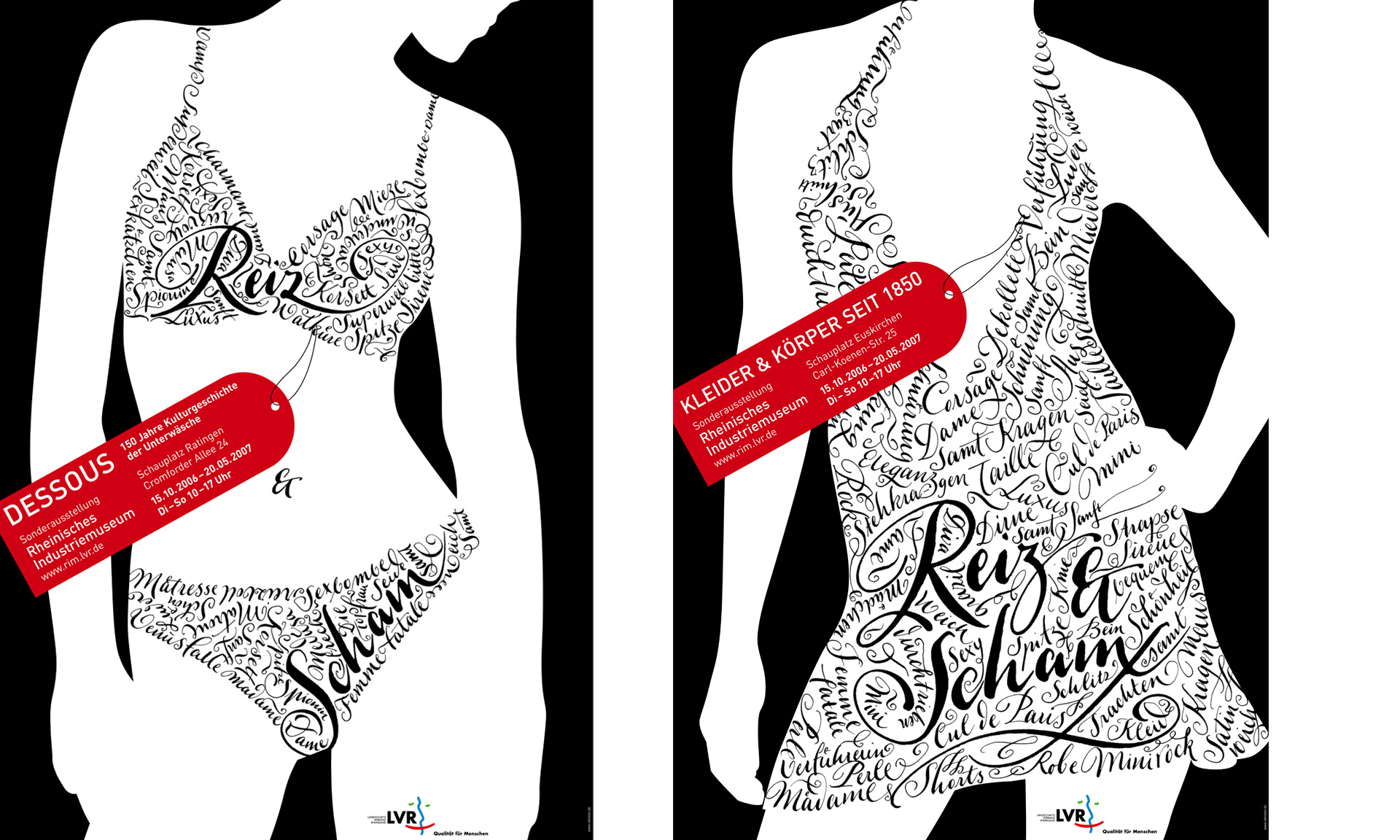
Reiz & Scham Ausstellungsplakate
Konzeption und Gestaltung:
Oktober Kommunikationsdesign, Bochum
Leistung:
Kalligrafische Umsetzung der Wäschestücke, Lieferung der Feindaten.